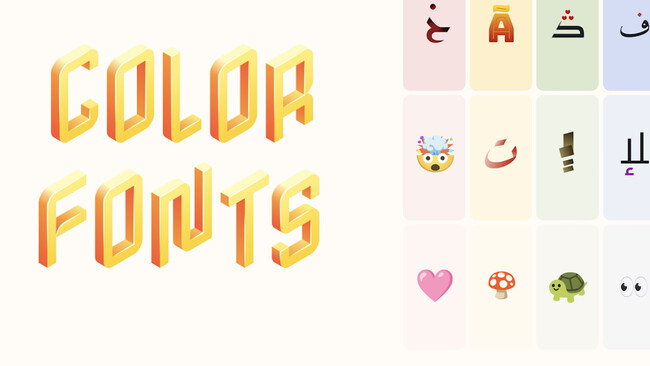
Es probable que nunca hayas oído hablar de las 'fuentes de color' (también conocidas como 'fuentes cromáticas' o como 'fuentes OpenType-SVG'), pero lo más seguro es que las estés usando todos los días a través de los emojis, una clase muy concreta de dichas fuentes. Se trata de un formato diseñado inicialmente por Mozilla y Adobe que se considera un estándar ya desde hace seis años.
Las fuentes o tipografías 'normales', las que hemos usado toda la vida en los procesadores de texto, tan sólo indican dónde va el color, en caso de que queramos cambiarlo manualmente desde el color por defecto (habitualmente, negro), pero las fuentes cromáticas habilitan la especificación de colores (y sombras, y texturas, y transparencias...) dentro del propio archivo de fuente.
Pero la última gran novedad en el campo de esta clase de tipografías es el desembarco del COLRv1, un formato vectorial binario (a diferencia de las fuentes de color originarias, basadas en mapa de bits), lo que permite escalar las letras sin que se pixelen.
Este formato nos facilita el uso de estas fuentes a la hora de diseñar un sitio web (aquí tienes algunos ejemplos), personalizando los degradados, las paletas de colores y la profundidad/grosor de las mismas, tal como se ve en las siguientes imágenes.
Desembarco en Google Fonts
Google ha anunciado ahora la incorporación de 9 fuentes de color a su popular servicio Google Fonts, que nos permite insertar tipografías en sitios web sin necesidad de subir a los mismos ningún fichero *.ttf. "Estamos tan entusiasmados con las fuentes de color que incluso hemos agregado un filtro de búsqueda específico para ellas en Google Fonts", admiten en la compañía.
La mayoría de estas nuevas 9 fuentes están enfocadas, en su mayor parte, a dar soporte al alfabeto árabe (aunque también son compatibles con el latino), si bien incluye también novedades como:
- Noto Color Emoji, la versión cromática (y ampliada) de Noto Emoji, que nos permitirá personalizar la coloración de todos los emojis que se te ocurran.
- Nabla, inspirada en los juegos de computadora isométricos gracias a la capacidad de COLRv1 para dotar de perspectiva a las fuentes.
- Bungee Spice, un "nuevo miembro de la familia Bungee inspirada en la señalización urbana incluye múltiples degradados y paletas de colores para que juegues con ellos".